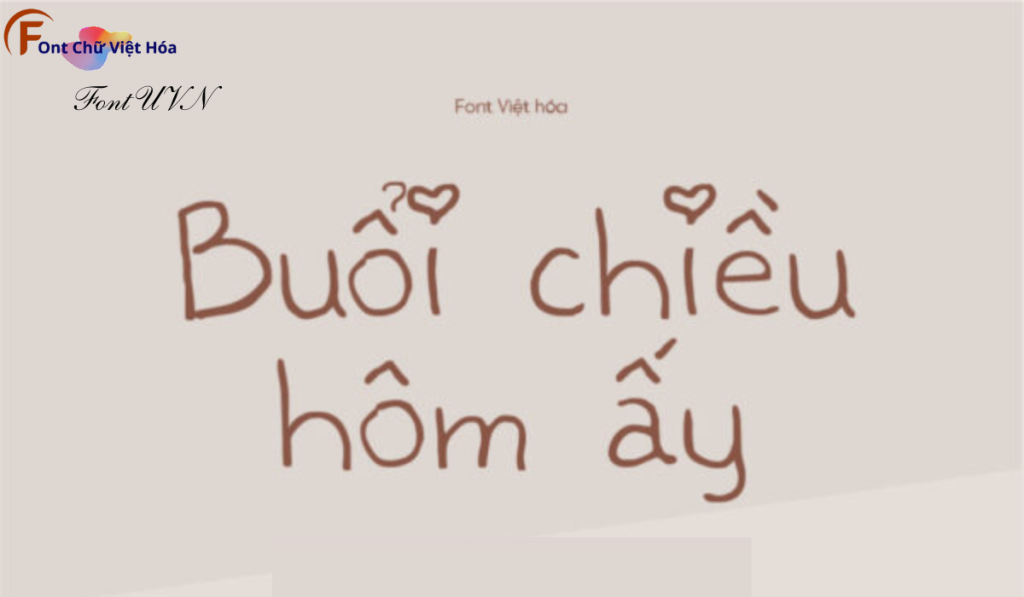
Font UVN Kaileen Việt Hóa
Font UVN Kaileen Việt Hóa là một font chữ viết tay cá tính, thuộc bộ font UVN. Được thiết kế với mục tiêu mang lại sự mềm mại và thanh thoát, font này lý tưởng cho các dự án thiết kế như thiệp mời, logo, và bao bì sản phẩm. Với các nét chữ uyển chuyển và độ dày đều đặn, Font UVN Kaileen Việt Hóa không chỉ dễ đọc mà còn tạo cảm giác thân thiện và gần gũi. Việc Việt hóa font giúp người dùng dễ dàng sử dụng trong các thiết kế tiếng Việt, mang lại sự tiện lợi và thẩm mỹ cao.